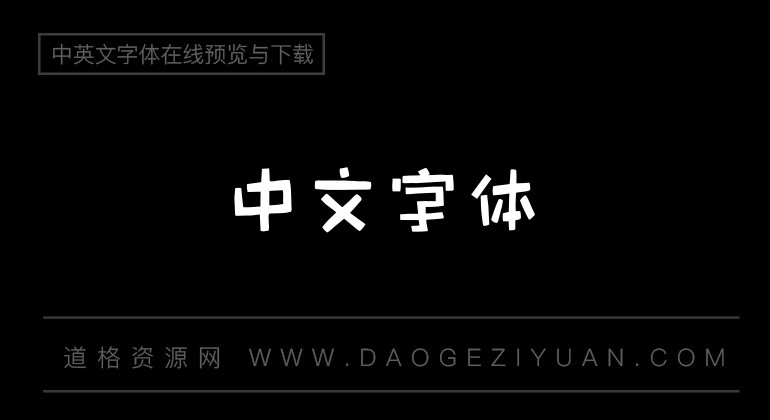
腾祥童话体简是一款简洁明快的童话体字体,由腾祥字体设计团队推出。它采用了童话般的风格,字体结构清晰,笔画流畅,拥有良好的可读性,给人以温馨、浪漫的感觉。腾祥童话体简适用于各种儿童类文字,如儿童读物、漫画书、故事书等,可以为文字增添童趣,使文字更加有趣。文件名:TengXiangTongHuaTiJian-2.ttf
腾祥童话体简是一款非常不错的手写艺术字体,具有很好的视觉感,适合于文化类的宣传设计、商业类品牌的广告和产品包装设计以及个性化文字排版等较多场景。